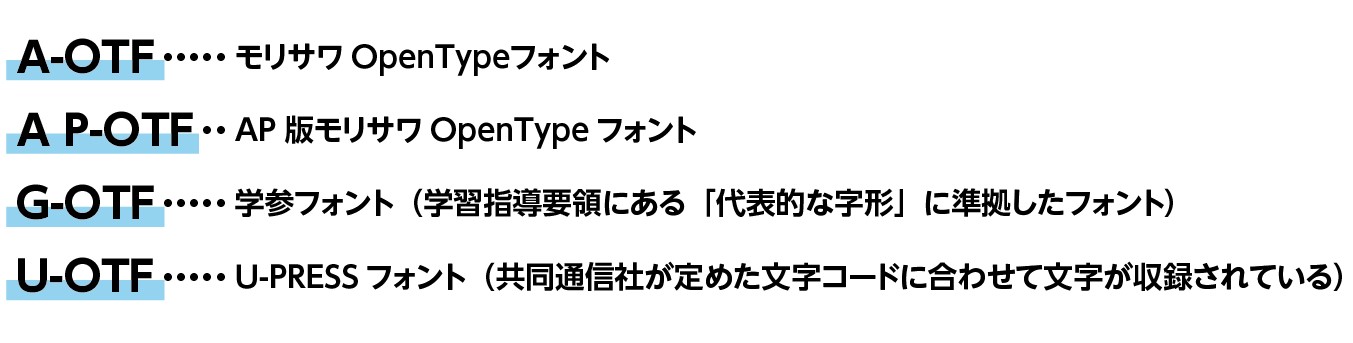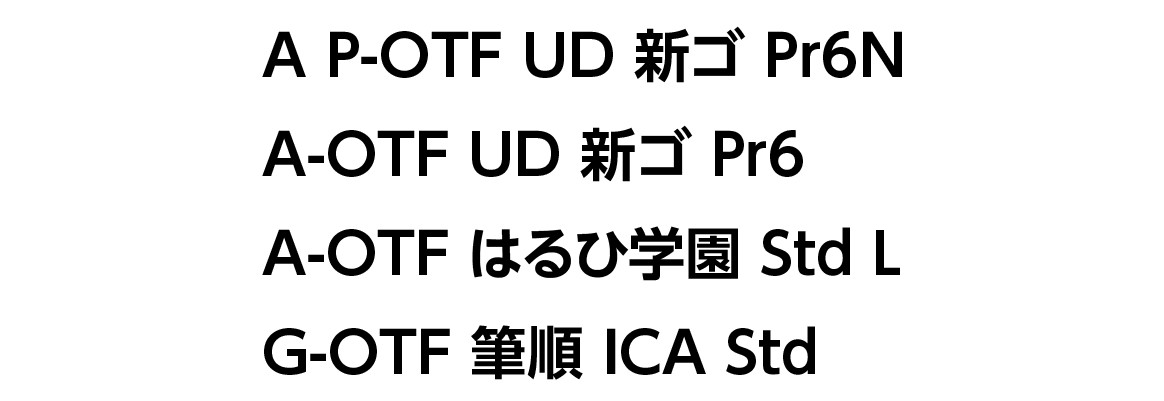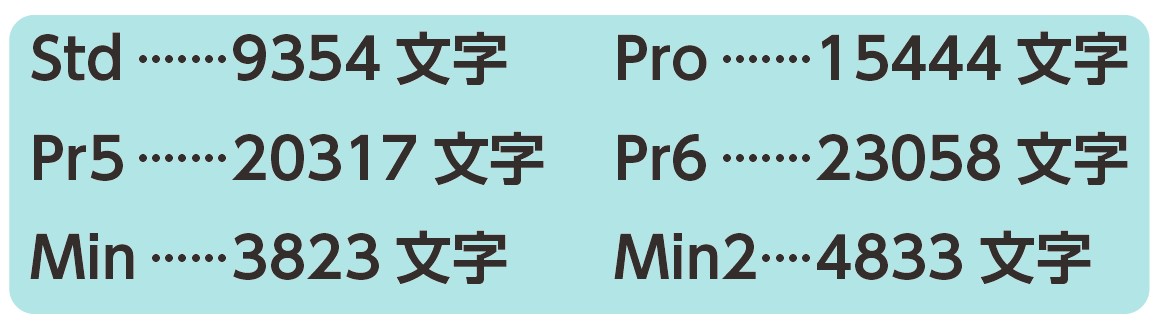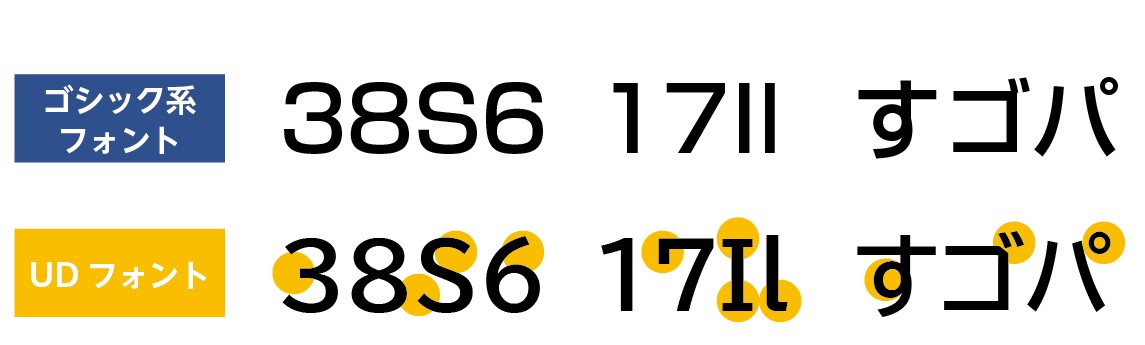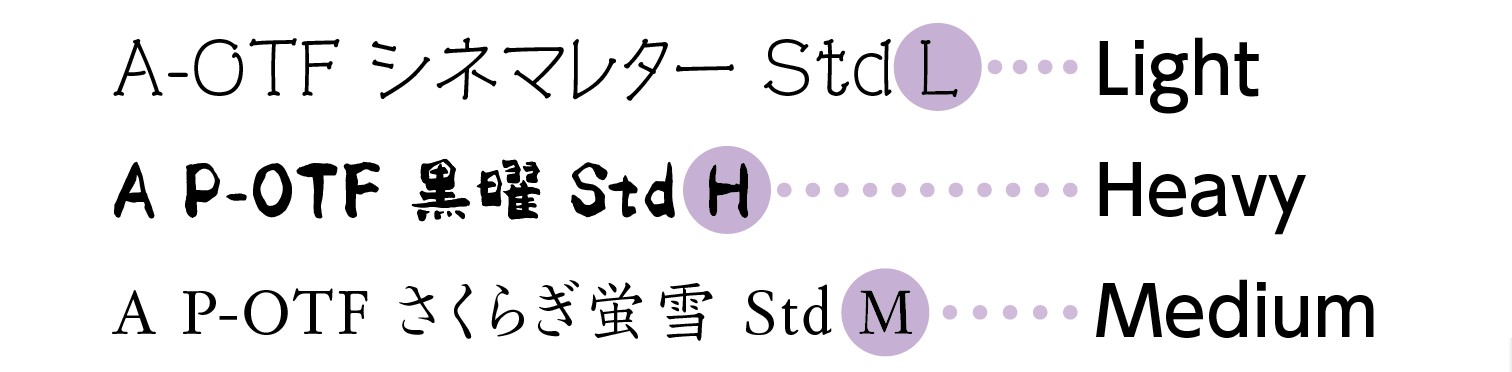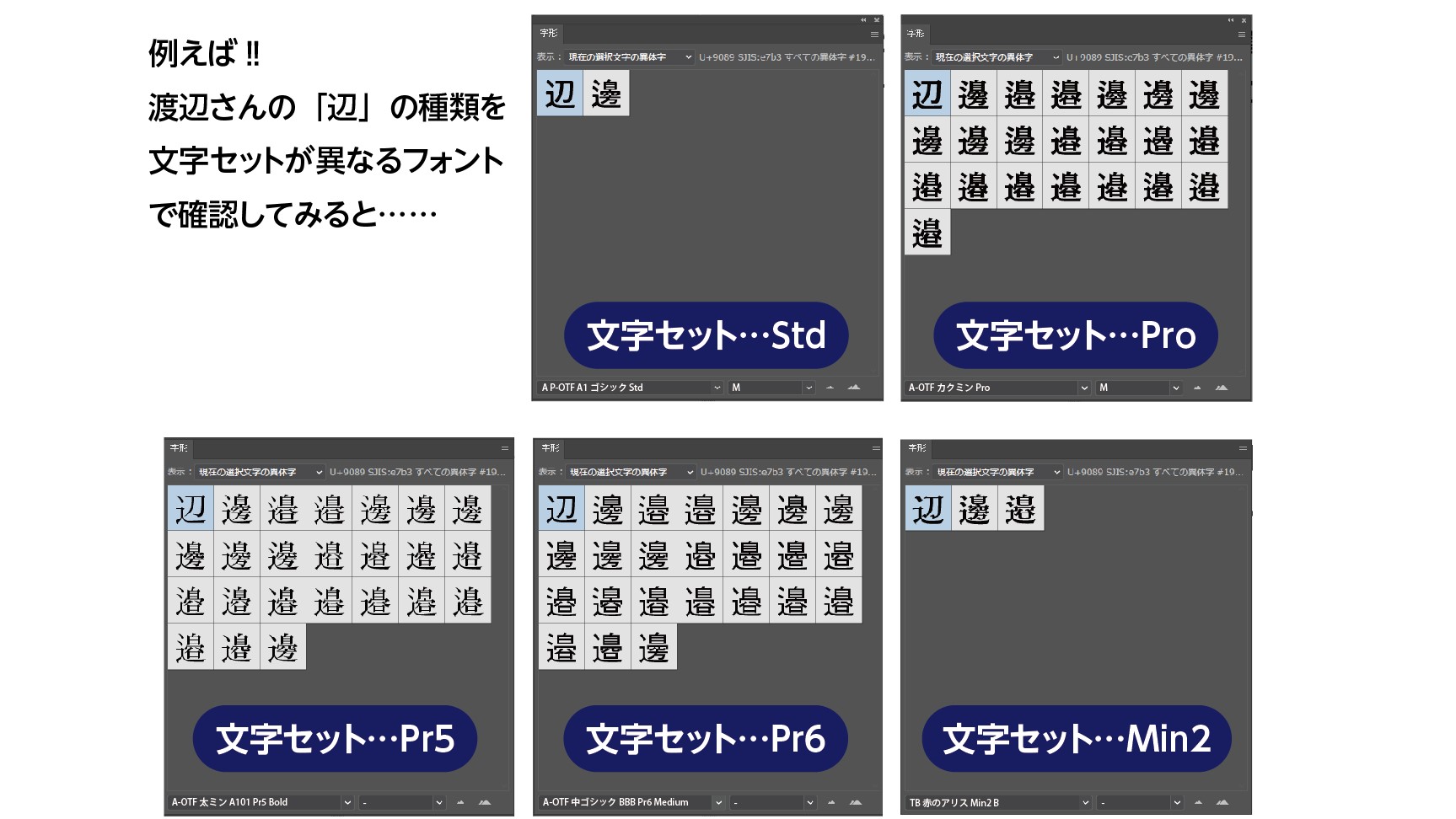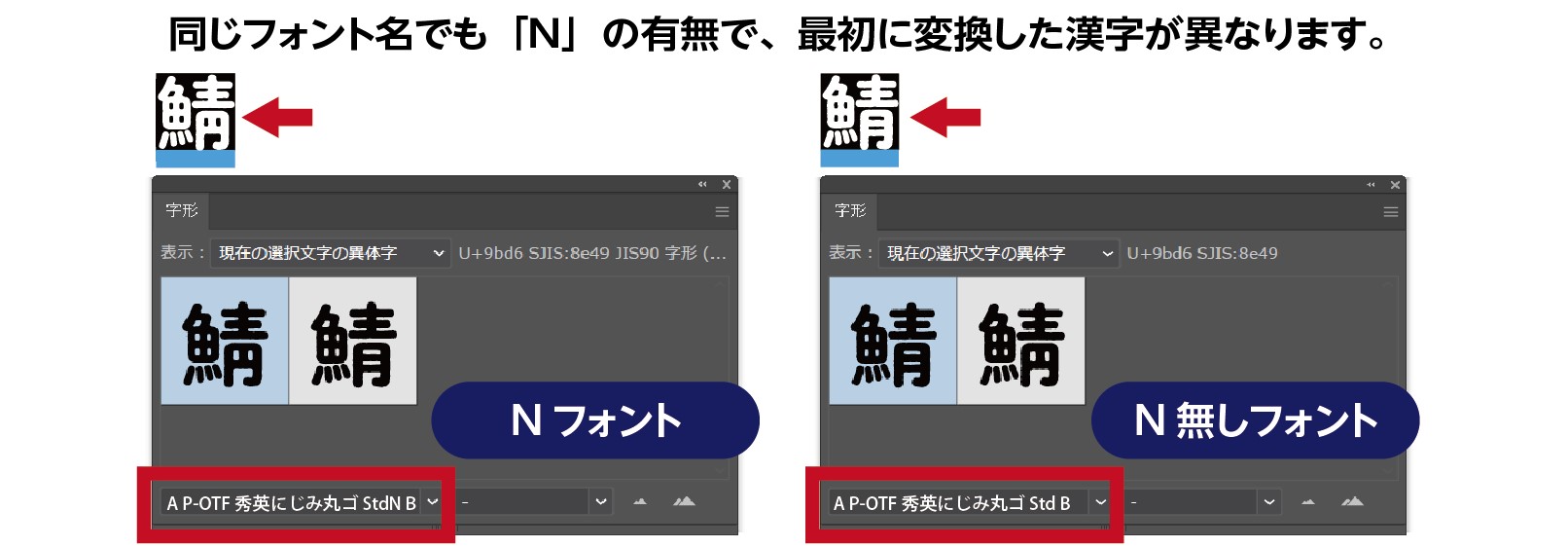
フォントの表記名、読み解いていきます~!
毎年新しいフォントが出てくるのは嬉しいですが、パソコンにフォントをたくさん入れていると、フォント一覧で「名前が同じものが複数並んでいる……!?」と思った方もいるのではないでしょうか。
名は体を表すと言うように、フォントの名前はもちろん、フォントの名前の前後についているアルファベット達にも意味があります。フォントの表記名の見方を知っていると、フォントを選ぶ時の参考になることも……!
今回は弊社からご提供しているフォントを例に、フォントの表記名を読み解いていきます。
はじめに
Illustratorなどでフォントを選択する際、フォントの表記名はこのように表示されます。
複数のパーツ(「A-OTF」や「Pr6」など)で構成されており、それぞれフォントの仕様などを表しています。各パーツごとにどのような情報を表しているのか、これからご説明していきます!
1.フォントの名前
まずはフォントの表記名のメイン!ズバリそのものフォントの名前については、「A-OTF」「A P-OTF」等の次にくる部分が該当します。フォントのデザイン名を表している箇所ですね!
「はるひ学園」など、ユニークな名前がついているものもあります。
フォントの名前の後に「KL」「KS」「KO」「NT」と付いている場合がありますが、これは「かな」に関するものです。(例えば……A-OTF リュウミン Pro L-「KL」、A-OTF リュウミン Std L-「KS」、A-OTF UD新ゴ「NT」 Pr6 など)
・KL…大がな(かなが大きめ)
・KS…小がな(かなが小さめ)
・KO…オールドがな(活字書体のデザインを生かし、縦長のプロポーショナルの文字が多い)
・NT…ネオツデイをベースにしたかなを使用
ちなみに……
「筆順」と付いているフォントは、書き順に沿ったストロークごとに一文字として文字を書いていく過程を収録しているフォントです。
2.フォントの表記名の最初についてるアルファベット
これは、メーカーの区別やフォントのファイル形式を表しています。 頭に「A-OTF」「A P-OTF」がついていたら、「モリサワのフォントなんだな~」と思ってください!
AP版はペアカーニング情報を搭載している他、一部グリフのデザイン調整を行っています。
そのため、「A-OTF」と「A P-OTF」は、後に続くフォントの名前が同じだとしても、異なるフォントとしての扱いとなり互換性がないのでご注意ください!(例えば……「A-OTF UD新ゴ Pr6N」と「A P-OTF UD新ゴ Pr6N」など)
「A-OTF」などの後に「UD」と書いてあるフォントは、ユニバーサルデザインに配慮したデザインであるUDフォントを表しています。フォントを探すときに「UDに配慮されているフォントを使用したいかどうか」というところでも絞り込むことができますね!
UDフォントと通常のゴシック系のフォントのデザイン比較例
下:UDフォント(識別性が向上するように、文字の中の空間が広い・濁点半濁点が大きめなデザイン設計となっています)
フォントの名前の後に付いているアルファベット達は、文字セットを表しています。
文字セットとはフォントが持っている(収録している)文字数を表しています。フォントの名前が同じものでも、文字セットが異なる場合があるのでご注意ください!
書籍の本文など様々な漢字を使用するときは、なるべく収録文字数が多い文字セットのフォントを選択することをオススメします!
Illustratorの字形パネルによる比較例
■Nフォント
文字セットの後に「N」がついているフォントは「Nフォント」「N付フォント」と呼ばれています。(例えば……「A-OTF リュウミン Pr6N」「A P-OTF 剣閃 StdN B」など)
Nフォントとそうでないフォントは、キーボードなどで文字入力した時点で最初に表示される字形が異なります。
Illustratorの字形パネルによる画面例
右:秀英にじみ丸ゴStdの「Nが無いフォント」
パソコンの画面表示の進化などの兼ね合いもあり、時代によって基本となる字形が異なっておりました。
基本となる字形はJISで定められており、「JIS90」と「JIS2004」のどちらの字形を最初の文字入力時に採用するかを「フォント名のNの有無」で区別ができるということです!
Nフォントの文字セットごとに収録している文字数
2019年10月24日以降にリリースしたAP版の新書体のうち、ProN, Pr5N, Pr6Nは縦組み用と横組み用の令和合字(㋿)を収録しています。そのため、各文字セットにおいて上記表より2つ文字数が多くなります。また、StdNでは、横組みの合字を収録しているため1つ文字数が多くなります。
末尾に付いているアルファベット(「L」「H」など)はウエイトを表しています。
ウエイトの表記は下記のようなものがあります。
L→Light  R→Regular  M→Medium  B→Bold  EB→Extra Bold  H→Heavy  EH→Extra Heavy  U→Ultra
W1~9→大きい数字のものほど太いウエイト
ウエイトを段階的に変えて作られた書体のグループを「ファミリー」と言います。「黎ミン」というフォントは2012年に世界で最も文字数の多い書体ファミリー(ファミリー合計783972文字!)に認定されています!
ファミリーが豊富な書体は、見出しや本文など要素ごとにウエイトを微調整できるので便利ですよね~。